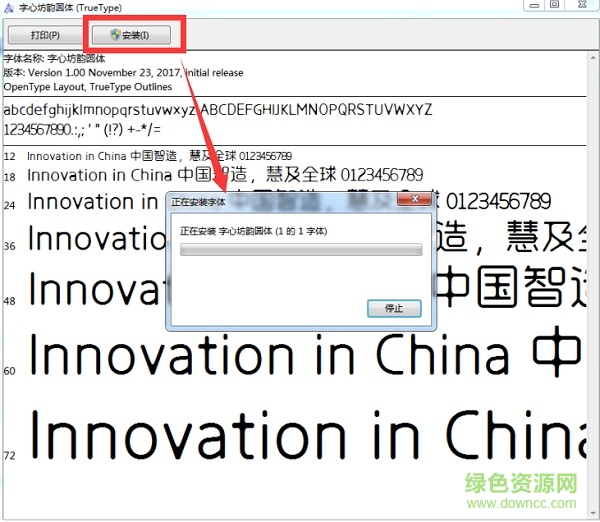
字心坊韻圓體字體是字心坊字體中比較規(guī)整的一款字體應(yīng)用。此字體書寫的文字非常不僅僅美觀大氣,還帶有靈動(dòng)性。在廣告設(shè)計(jì)上用到的很多!有需要這款字體的朋友快來綠色資源網(wǎng)下載吧。
字體筆畫設(shè)計(jì)自然美觀,字形簡(jiǎn)約,曲線優(yōu)美,優(yōu)雅圓潤(rùn),具有較大范圍的應(yīng)用空間。字體個(gè)性鮮明,字形特點(diǎn)時(shí)尚新穎,同時(shí)融入古風(fēng)結(jié)構(gòu),靈活多變的線條造就此款字體的與眾不同。